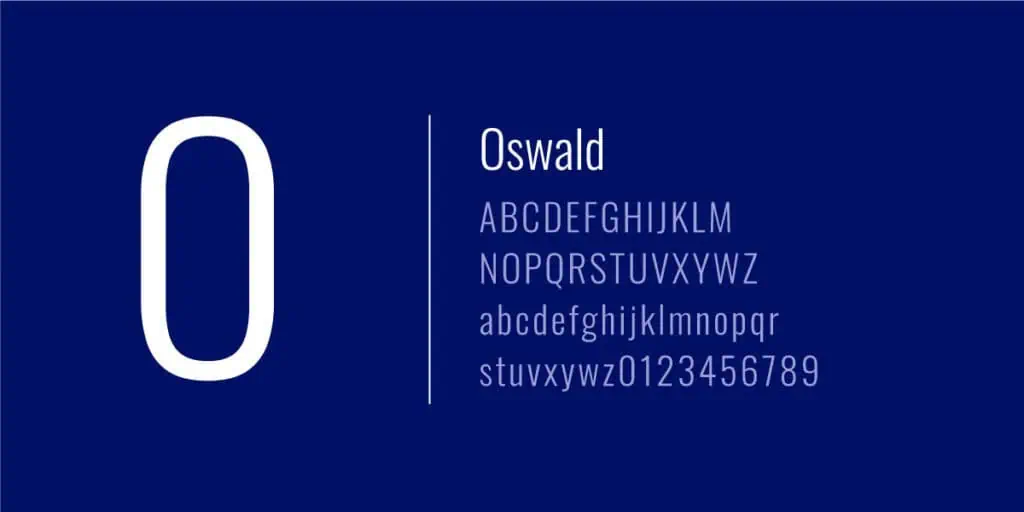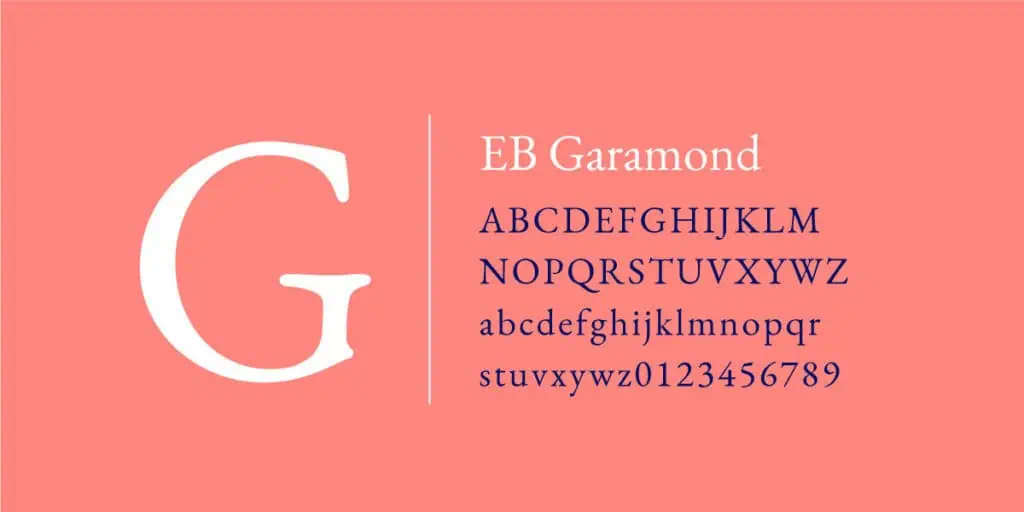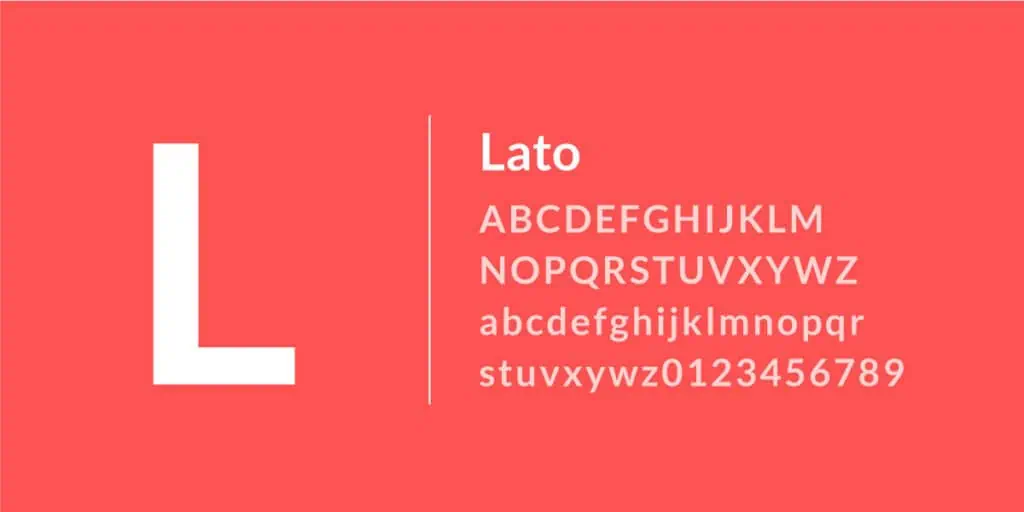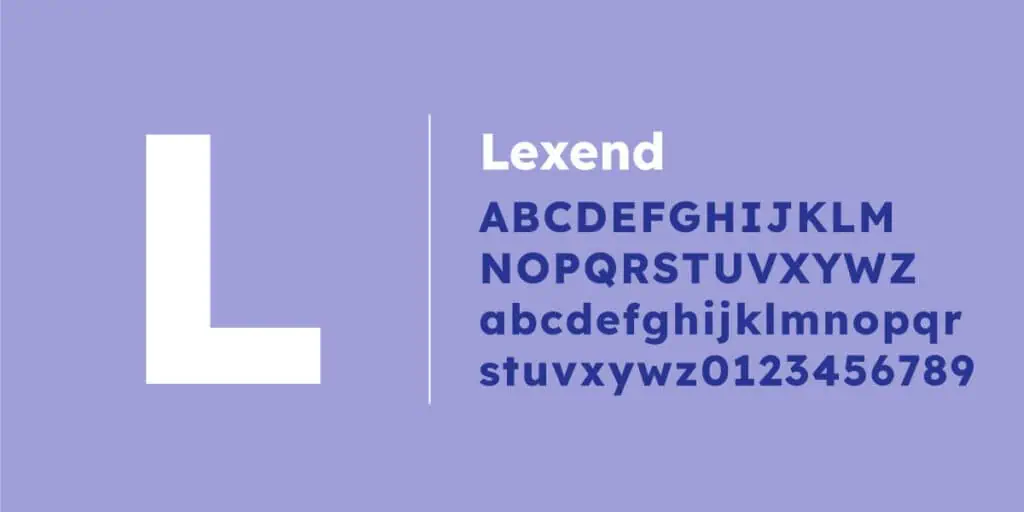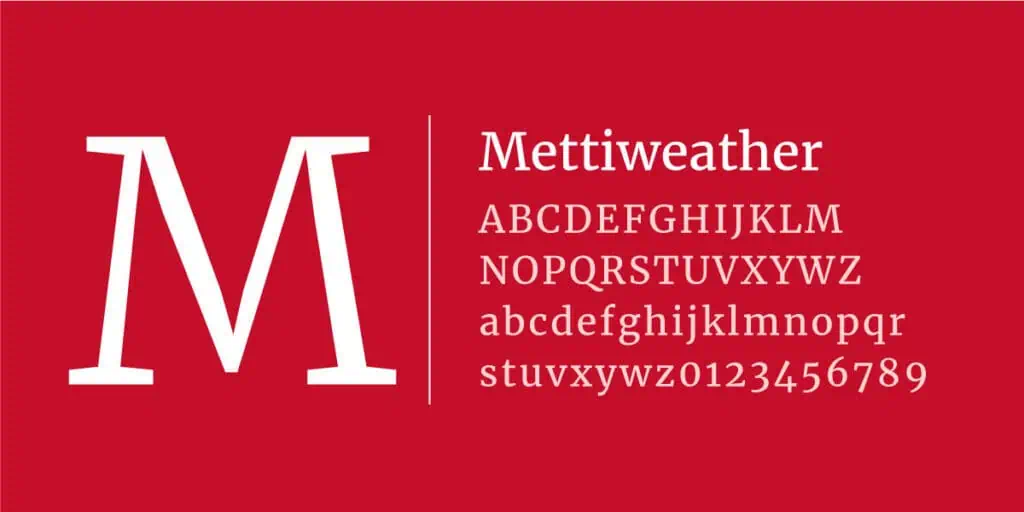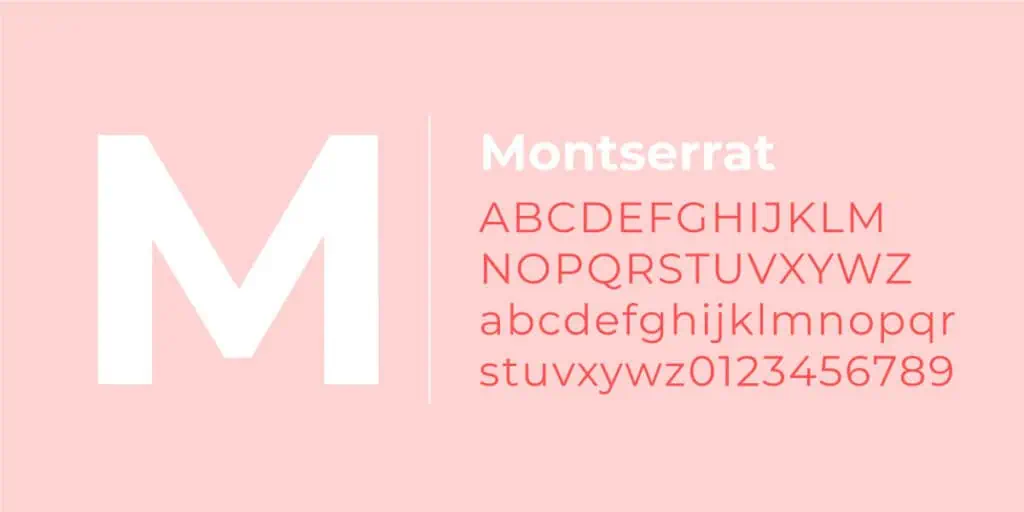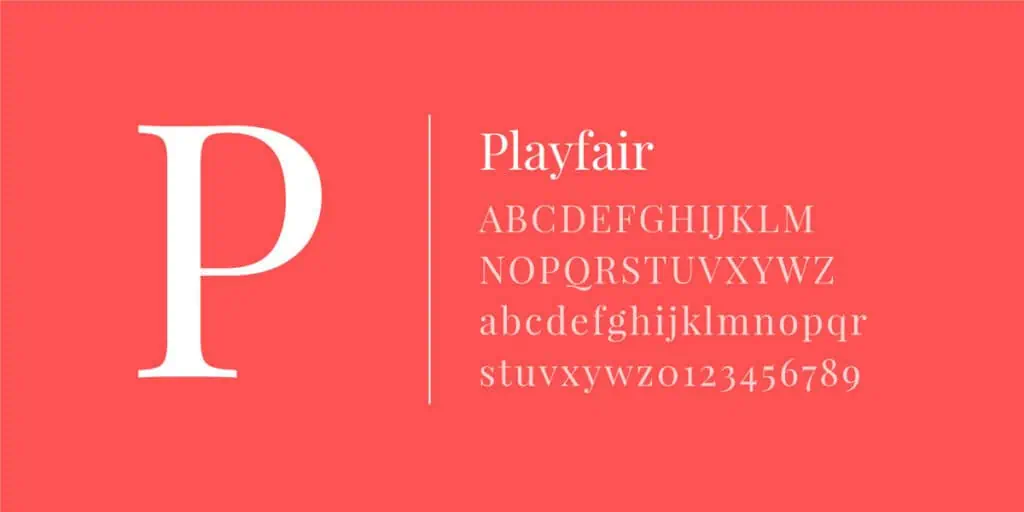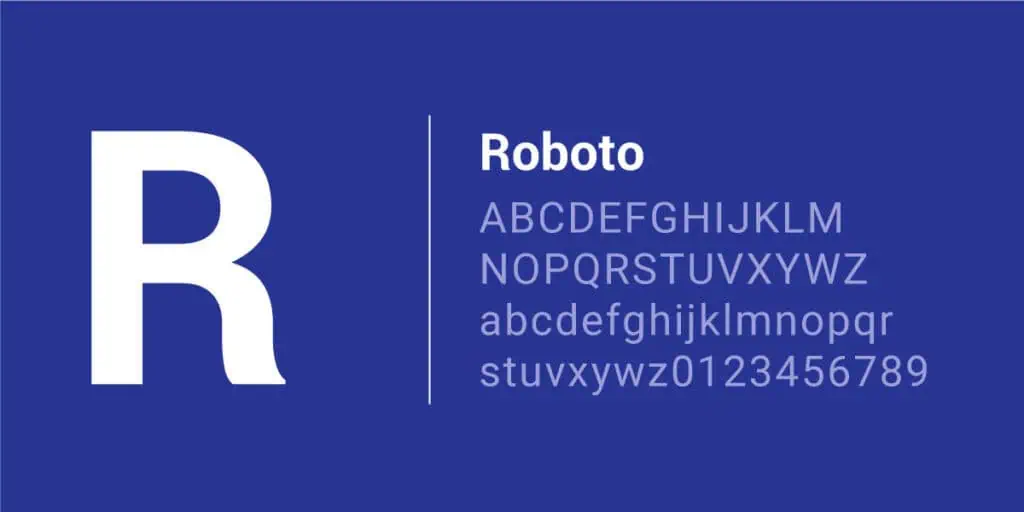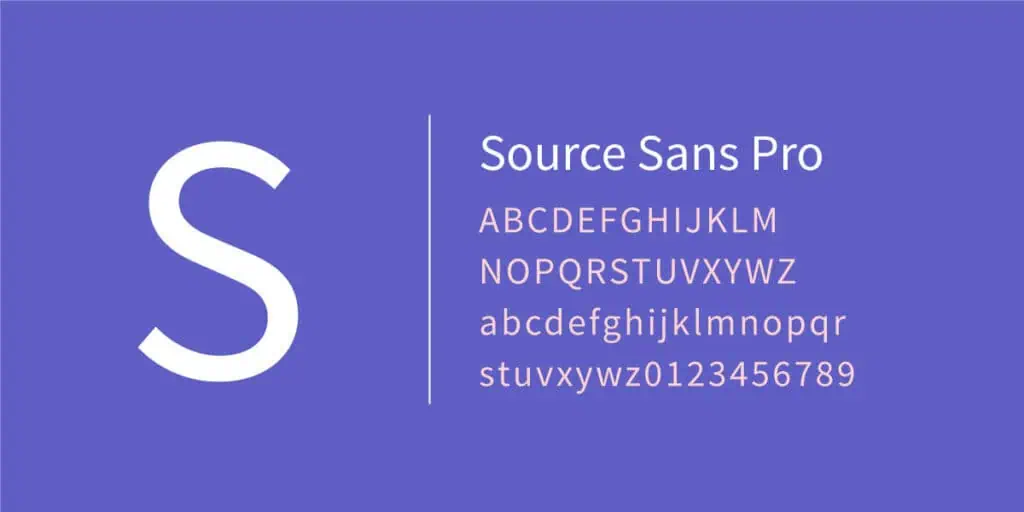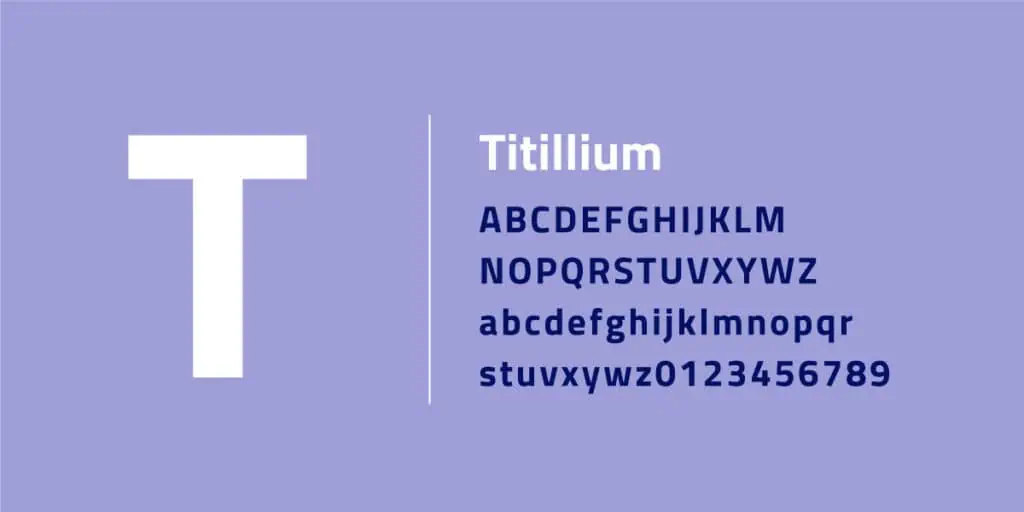
Tra gli aspetti più importanti del tuo sito web c’è sicuramente l’aspetto visivo e la scelta del font è fondamentale. Il font è un elemento importante nel progetto grafico perché comunica personalità ed è tra gli elementi che identificano la tua brand identity. Inoltre la scelta di un font piuttosto che un altro può rendere più o meno leggibile lunghi paragrafi di testo.
Prima di iniziare un progetto web ti consigliamo di scegliere con cura il font che utilizzerai non solo per una questione di immagine ma anche di compatibilità con l’HTML.
Cosa sono i Web Font?
La tipografia è una materia ricca di storia ma i font che conosciamo oggi hanno una vita recente e nascono con la comparsa dei computer e di internet. I caratteri tipografici, sui dispositivi digitali hanno avuto bisogno di alcuni adattamenti per la resa a video ma quando sono stati messi in commercio dispositivi con dimensioni video differenti, tutto si è complicato.
Esistono moltissimi tipi differenti di font, alcuni sono più adatti per la stampa altri invece sono progettati proprio per rendere migliore la leggibilità a video. Per i progetti web bisogna inoltre tener conto che non tutti i font sono compatibili con i software in uso e scegliendo font ‘speciali’ si corre il rischio che questi vengano sostituiti con dei font ‘web safe’ cioè font presenti nella maggior parte dei computer come ad esempio l’Arial, il Verdana, il Times New Roman, il Tahoma.
Per un buon web design consigliamo di scegliere tra i web font, caratteri tipografici progettati appositamente per essere visualizzati correttamente nel web dai diversi dispositivi in commercio e in uso su molti programmi tra cui quelli di posta elettronica.
La differenza principale tra i font desktop ed i web font è che i secondi per essere utilizzati potrebbero aver bisogno di essere caricati su un server e usati nel web.
I web font sono progettati per adattarsi alle diverse dimensioni degli schermi e possono essere formattati con i CSS per ottenere il grassetto o il corsivo, modificare colori e dimensione.
Anche se i web font non sono installati nel tuo dispositivo desktop o mobile e in quelli dei tuoi utenti, ci sono dei modi speciali perché vengano correttamente visualizzati a chi visita il tuo sito web.
Un modo è quello di caricarli su un server oppure utilizzare un servizio di web font hosting che permette di incorporare i font senza doverli scaricare.
Come aggiungere un Font in HTML
Alcuni font non sono fatti per essere usati sul web, quindi quali possono essere inseriti nel vostro sito HTML?
Essenzialmente, sul vostro sito potete usare qualsiasi font scaricabile. Tutto quello che dovete fare è caricarlo e configurarlo correttamente, e questo dovrebbe bastare per visualizzarlo sul vostro sito web.
Tecnicamente è possibile utilizzare qualsiasi font tu voglia ma questo non significa sia una buona idea.
Scegliere dei font adatti alla visualizzazione nel web significa progettare la User Experience invece di mettere al primo posto solo la questione estetica. Inoltre alcuni font sono visibilmente inadatti per una visualizzazione sul web, questo non succede se si sceglie un web font.
Oggi è possibile scegliere font su portali host, con piani gratuiti e a pagamento, che permettono di utilizzare i font sul tuo sito web attraverso una chiamata HTML.
Per essere caricato correttamente il vostro font dovrà avere una delle seguenti estensioni file:
- TTF
- OTF
- WOFF/WOFF2
- SVG
- EOT
Con questi tipi di file, potrai utilizzare i font in tutto il tuo sito web e di stilizzarli con HTML e CSS.
I font ‘web safe’ sono chiamati così perchè funzionano universalmente in tutti i browser e programmi.
Cosa sono i Font sicuri per il Web?
Uno dei problemi più comuni nel web è la mancanza di garanzia che il tuo font venga visualizzato correttamente nel web. A differenza del design per progetti stampati in cui una volta terminato il progetto grafico il file è destinato alla stampa, i browser devono scaricare i web font ogni volta che qualcuno apre una pagina web. Se i vostri font non riescono a caricarsi, potreste ritrovarvi con un sito web vuoto e sembrare rotto.
Per questo motivo, alcuni web designer preferiscono scegliere solo tra i font sicuri per il web (o font “web safe”). I font ‘web safe’ sono preinstallati sulla maggior parte dei sistemi operativi, e questo garantisce che possano essere visualizzati correttamente su tutti i dispositivi di massa. Questi font hanno inoltre il vantaggio di caricarsi molto più velocemente dei font web, che in alcuni casi possono invece essere più lenti.
Se il tuo obiettivo è massimizzare al massimo le prestazioni web e assicurarti che il tuo sito sia visualizzato con i font corretti allora i font ‘web safe’ fanno per te.
EB Garamond nasce per essere un eccellente Garamond classico. È un progetto contributivo per creare un revival dei famosi caratteri umanistici di Claude Garamont della metà del XVI secolo. Questa versione digitale riproduce fedelmente il disegno originale di Claude Garamont. La fonte per le forme delle lettere è una scansione di un esemplare noto come “esemplare Berner”, composto nel 1592 da Conrad Berner, genero di Christian Egenolff e il suo successore alla tipografia di Egenolff. Questo esemplare mostra i caratteri romani del Garamont e il corsivo di Granjon a diverse dimensioni. Da qui il nome di questo progetto: Egenolff-Berner Garamond.